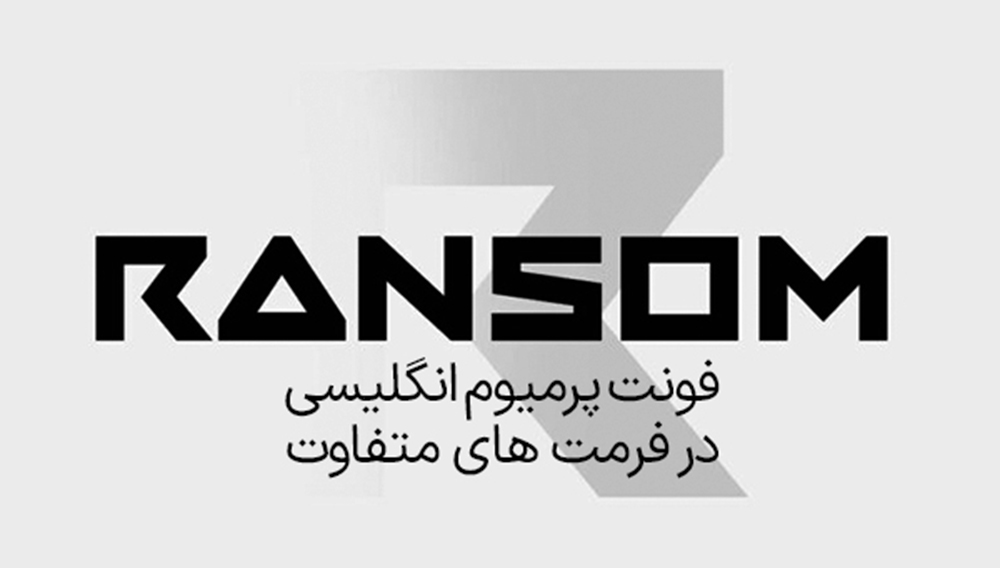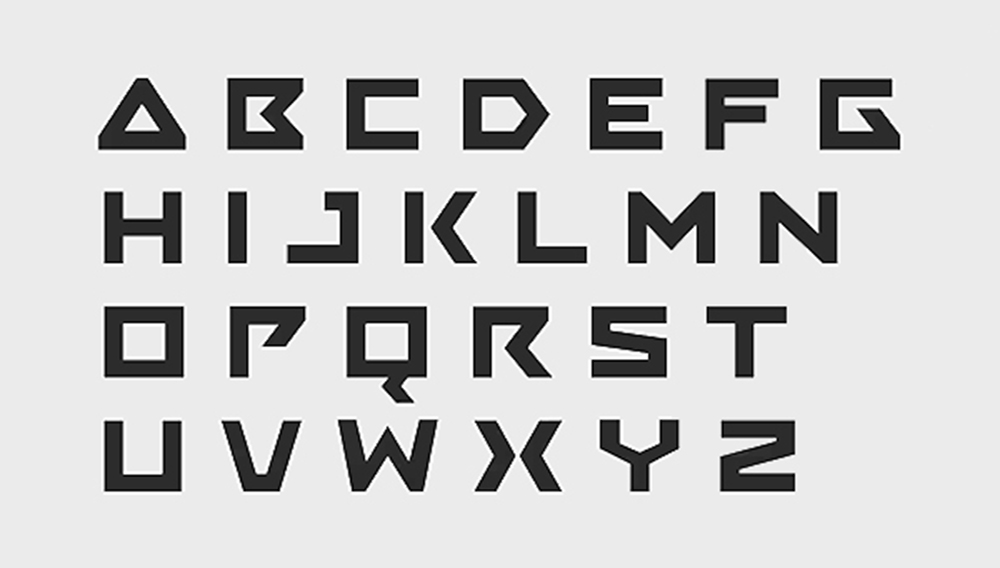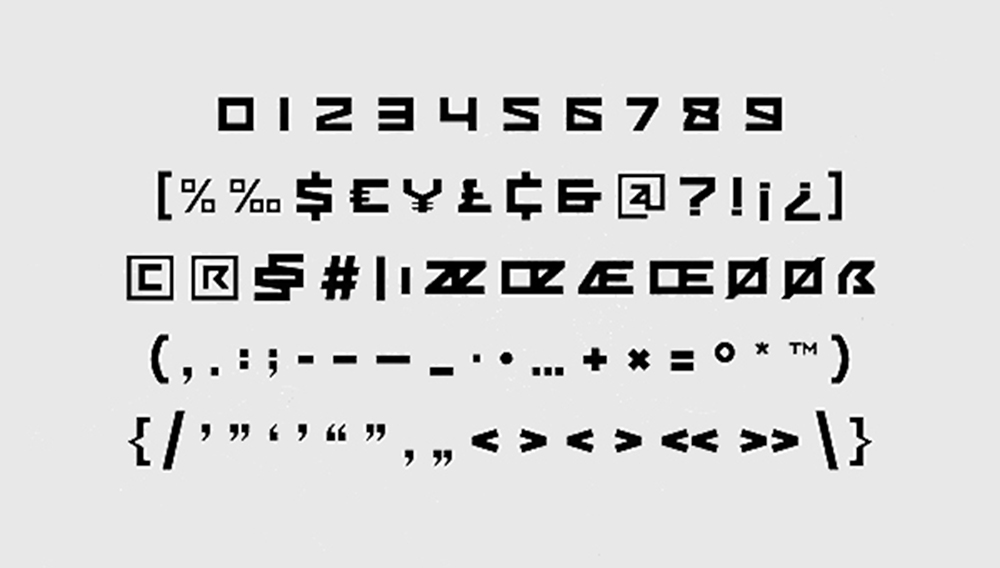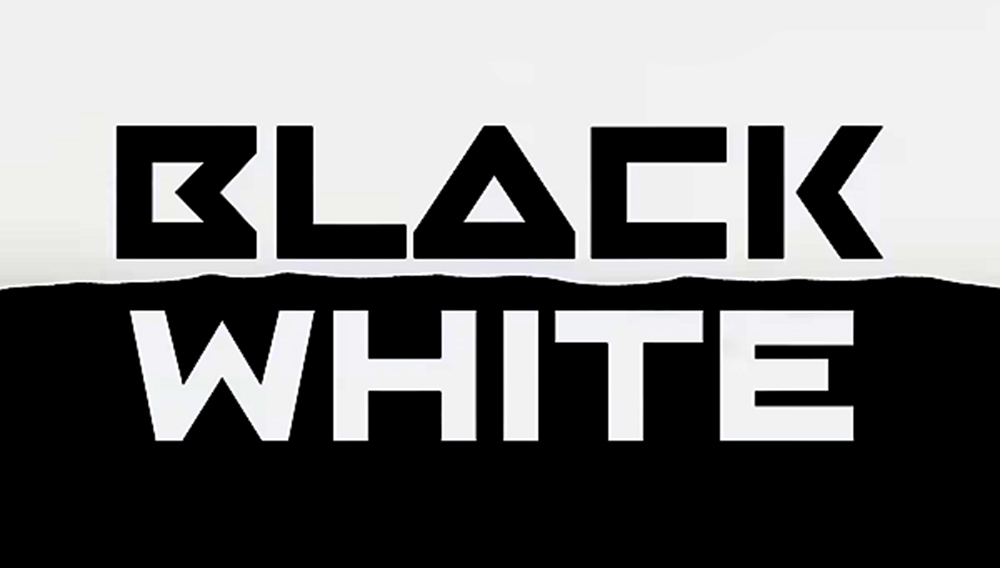
دانلود فونت انگلیسی Ransom Font
فونت پریمیوم Ransom یک فونت فناوری مدرن است که برای نیازهای فناوری، علمی تخیلی، مدرن و برجسته تر نیازهای تایپوگرافی با سبک آیندهنگر، با سبکهای مدرن…
فونت پریمیوم Ransom یک فونت فناوری مدرن است که برای نیازهای فناوری، علمی تخیلی، مدرن و برجسته تر نیازهای تایپوگرافی با سبک آیندهنگر، با سبکهای مدرن که طراحی شما را به یاد ماندنیتر میکند، ایجاد شده است.
فونت Ransom یک فونت انگلیسی فانتزی، با سبک اکشن جسورانه و مدرن طراحی شده است که می توان از آن برای ایجاد هر پروژهای که ایده اصلی را نشان میدهد استفاده کرد.